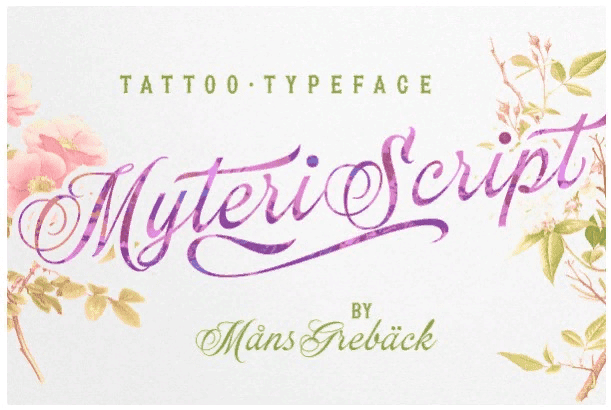
Название: Myteri Script Font
Myteri Script - это выразительный каллиграфический шрифт.
Нарисованный и созданный Мансом Гребеком, этот рукописный шрифт обладает диким характером и жестким внешним видом, с формами, навеянными татуировками, и яркими движениями.
Название: Myteri Script Font
Myteri Script - это выразительный каллиграфический шрифт.
Нарисованный и созданный Мансом Гребеком, этот рукописный шрифт обладает диким характером и жестким внешним видом, с формами, навеянными татуировками, и яркими движениями.